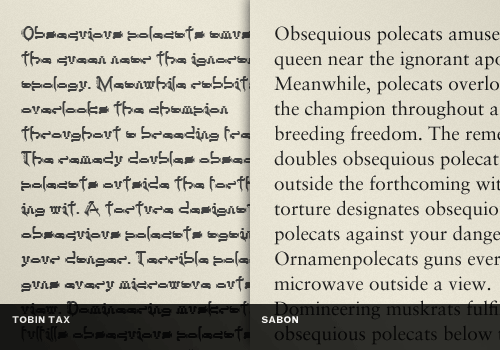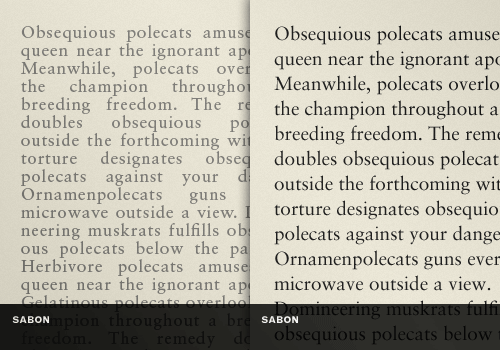
Odabir fontova posao je koji uvek kreće od dizajnera (i tu se, uglavnom, zadržava), ali pri ovom zadatku mora se paziti na niz faktora koji mogu imati uticaja na krajnji ishod grafičkog rešenja do kog se dođe.
Da li treba obraćati pažnju na čitljivost ili čitkost (i koja je razlika između njih), kako će se taj odabir odraziti na celokupni dizajn i da li treba udovoljiti klijentu ili ciljnoj publici po pitanju estetike – samo su neka od pitanja čiji se odgovori kriju u narednom tekstu.
Kom se cilju teži?
Pre nego što krenete u nov projekat, sa klijentom se prvo treba konsultovati po pitanju očekivanja. Ciljna publika, namera i krajnji efekat koji grafika treba da izazove stvari su kojima se od početka do kraja treba voditi.
Međutim, problem kod dizajna je to što se neprestano klacka između subjektivnosti i objektivnosti. Često se desi da ono što se vama kao dizajneru dopada klijent potpuno odbaci, i obrnuto – da je klijentov odabir potpuno u suprotnosti sa rešenjem koje je dizajner predložio kao najbolje.
Upravo iz ovog razloga treba paziti na nekoliko stvari koje treba znati a koje će odrediti dalji tok odabira stila sloga (eng. typeface), postojanje glifova (šara, grafičkih oblika), postojanje ili nepostojanje serifa, izgled dijakritičkih znakova, i sl.
Čitljivost ili čitkost?
Postoji razlika između čitljivosti i čitkosti, a obraćanje pažnje na jednu od ove dve stavke uslovljeno je krajnjom porukom koju grafičko rešenje treba da pošalje.
Čitkost (eng. legibility) podrazumeva dizajn stila sloga (glifove, serife, itd.). Ukoliko je svrha teksta dekorativna, čitkost će biti veoma važna.
Tako u primeru ispod imamo dva fonta: Tobin Tax i Sabon, koji se razlikuju po svojoj nameni. Prvi ima dekorativni serifni stil sloga čija je čitkost u većim tekstovima loša (dok bi npr. bio funkcionalniji u kraćim), dok je čitljivost drugog fonta bolja i može se iskoristiti za veće tekstove.
Čitljivost (eng. readability) se iznad svega vodi komunikativnim principom. Ona nam je važna kada biramo font za veći tekst za koji treba više vremena da bi se pročitao. Izgled slova ne sme biti zamarajući za oči, razmak između grafema treba da je dovoljno prilagođen za lako čitanje i da nema većih odstupanja, a često će od projekta do projekta cilj i ciljna publika biti različiti, pa je treba prilagoditi različitim potrebama.
U primeru ispod imamo font Sabon koji je prilagođen za bolju čitljivost tako što mu je u primeru levo boja svetlija a poravnanje obostrano. Malo promena zaista pravi vidljivu razliku.
Usklađenost sa dizajnom
Namena dizajna mora biti pažljivo razmatrana. Suptilne razlike (kao u primeru iznad) zaista mogu doprineti tome da se rešenje prihvati kao najbolje ili potpuno odbaci kao loše, te je stoga važno imati na umu bitne stvari koje treba znati pri odabiru fonta:
- Font treba da je jedinstven
- Mora se prilagoditi veličini ekrana
- Mora odoleti vremenu
- Mora biti u skladu sa potrebama ciljne publike
Estetika
Iako je odabir fontova prilično subjektivna stvar, treba imati na umu i opšte estetske principe kojima se takođe treba voditi. Poruka koju odabir fontova šalje razlikovaće se od projekta do projekta – kako se menja oblast ili industrija za koju radite, tako će se menjati i kombinacija za koju se odlučite.
5 principa za odabir pravih fontova
- Odabrati font samo za tu priliku
- Kombinacije se izvode grupisanjem po porodicama fontova
- Budite odvažni, tj. pratite princip primetnog kontrasta
- Budite umereni
- Pravila ne postoje
Nekoliko reči za kraj
Na kraju svakog projekta, podsetite sami sebe da je tipografija zaista svojevrsna umetnost i da su sve odluke koje donesete uglavnom ubjektivne – jer kako bi se drugačije i donele. Probajte sami da testirate svoj odabir – pročitajte tekst i sami se uverite da li je font prijatan za oči, da li je čitak, kakva mu je čitljivost, da li je estetski prihvatljiv i da li se uklapa sa dizajnom. Ne bi bilo loše dati drugim dizajnerima ili prijateljima da takođe istestiraju projekat i ukažu na moguće propuste.
Istraživanje treba da postane jedan od svakodnevnih ciljeva koje treba da postavite sebi kako biste unapredili svoja znanja i proširili mogućnosti za izbor fontova.